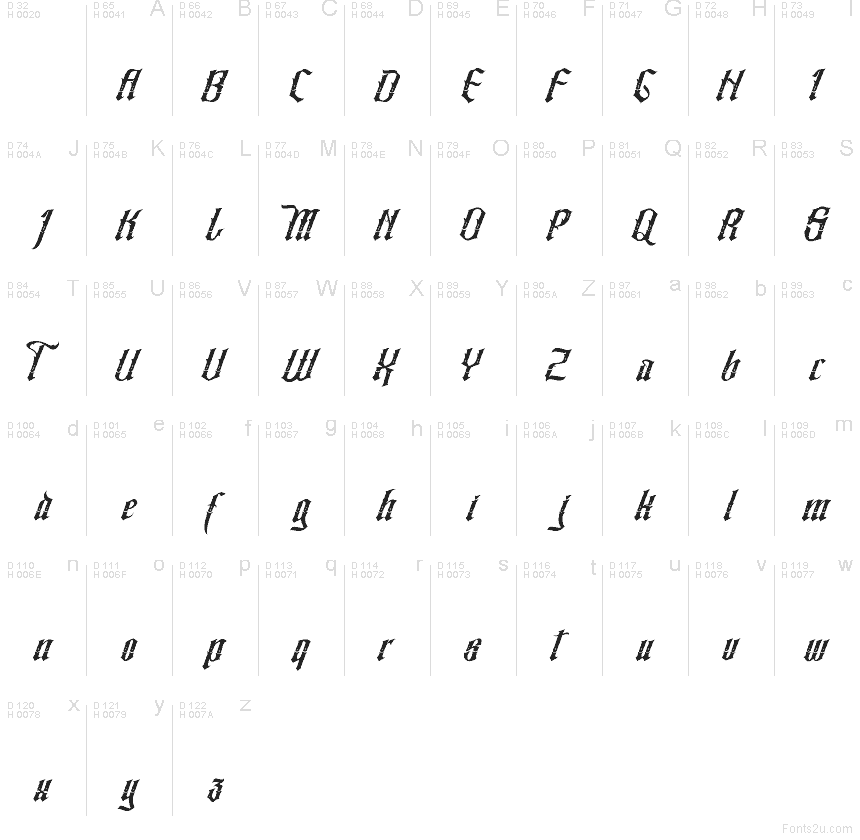
Konstans je moderní gotické písmo zdarma s útlým blackletter charakterem a výrazným rukopisným tahem. Písmena kombinují strmé, břity připomínající tahy s propojovacími smyčkami a špičatými zakončeními, což písmu dodává čilý, historizující rytmus, který působí živě, nikoliv ceremoniálně.
Hodí se pro titulky plakátů, hudební artworky, grafiku na oblečení, branding podniků a redakční nadpisy, kde má bezplatné písmo vnést trochu historické atmosféry, aniž by působilo zcela středověce. Použijte jej pro krátké fráze, loga nebo iniciály typu monogram, kdy chcete, aby kombinace ostré textury a plynulého pohybu odvedla většinu vizuální práce.